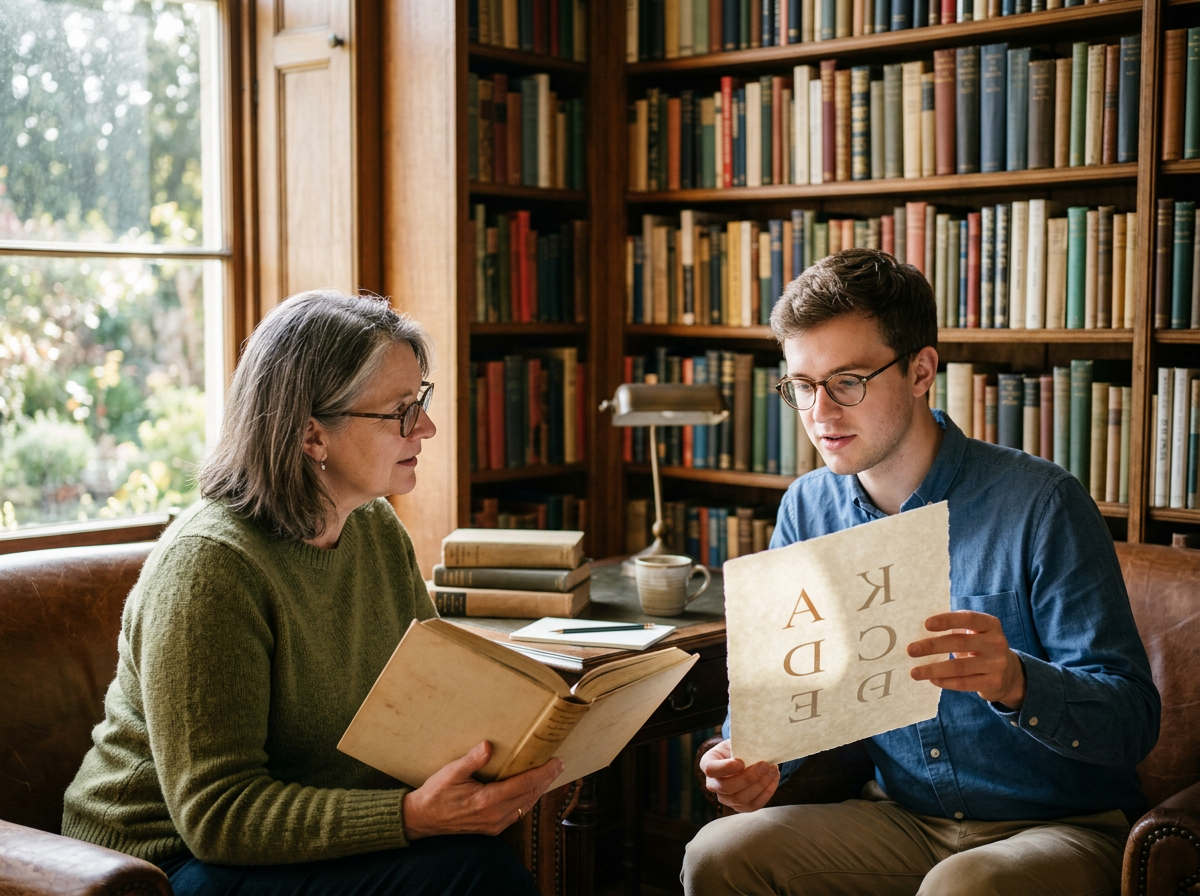
Welche Schriftarten eignen sich am besten für Bücher?
Die Wahl der passenden Schriftart für ein Buch stellt eine entscheidende Weichenstellung dar, die weit über bloße Ästhetik hinausgeht. Ein falscher Schriftsatz kann die Leseerfahrung erheblich beeinträchtigen, Ermüdungserscheinungen fördern und sogar die Botschaft des Textes verwässern.
Oftmals wird die Bedeutung der Typografie unterschätzt, dabei beeinflusst sie maßgeblich, wie flüssig und angenehm der Leseprozess verläuft. Eine gut gewählte Schriftart unterstützt den Inhalt, ohne selbst in den Vordergrund zu treten.
Dieser Leitfaden beleuchtet die kritischen Faktoren bei der Auswahl von Buchschriftarten und zeigt auf, welche Merkmale eine optimale Lesbarkeit gewährleisten, damit jedes Werk seine volle Wirkung entfalten kann.
Kurz zusammengefasst
- Serifen-Schriften wie Garamond oder Times New Roman bieten optimale Lesbarkeit für Fließtexte in Büchern.
- Die Schriftgröße sollte zwischen 10 und 12 Punkt liegen, der Zeilenabstand bei 120-145 % der Schriftgröße.
- Kontrast und Satzspiegel beeinflussen die visuelle Ermüdung stärker als die reine Schriftwahl.
- Für Überschriften und Zitate sind serifenlose Schriften oder Akzentschriften denkbar, jedoch sparsam eingesetzt.
Welche Eigenschaften machen eine Schriftart für Bücher lesefreundlich?
Lesefreundliche Schriftarten für Bücher zeichnen sich durch eine hohe Erkennbarkeit der einzelnen Zeichen und einen harmonischen Rhythmus im Fließtext aus, was die visuelle Verarbeitung des Textes durch das Auge erleichtert und Ermüdung vorbeugt.
Die primäre Funktion einer Buchschrift besteht darin, den Inhalt transparent zu vermitteln, ohne die Aufmerksamkeit auf sich zu ziehen. Eine gute Schriftart integriert sich nahtlos in das Leseerlebnis.
Die Rolle von Serifen und deren Wirkung
Serifen sind kleine Querstriche an den Enden der Buchstabenstriche, die traditionell als Lesehilfe dienen. verbinden die Buchstaben optisch zu Wörtern und Zeilen, was den Augenfluss über längere Textpassagen hinweg fördert.
Klassische Serifen-Schriften wie Garamond oder Caslon gelten seit Jahrhunderten als Standard für gedruckte Bücher. die feinen Details tragen zur Unterscheidbarkeit ähnlicher Buchstaben bei.
Die psychologische Wirkung von Serifen-Schriften wird oft mit Tradition, Seriosität und Beständigkeit assoziiert. Für Belletristik oder Sachbücher, die eine gewisse Autorität vermitteln sollen, sind sie daher eine bevorzugte Wahl.
Schriftgröße und Zeilenabstand optimal einstellen
Die Schriftgröße ist ein entscheidender Faktor für die Lesbarkeit; für den Haupttext in gedruckten Büchern hat sich eine Größe von 10 bis 12 Punkt etabliert, abhängig vom Schriftbild und der Zielgruppe.
Ein angemessener Zeilenabstand, auch als Durchschuss bezeichnet, verhindert, dass sich die Zeilen optisch überlappen und verbessert die Trennung der Textzeilen. Werte zwischen 120 % und 145 % der Schriftgröße sind hierfür praxisbewährt.
Ein zu geringer Zeilenabstand führt zu einem dichten Textblock, der das Auge überfordert, während ein zu großer Abstand den Textfluss unterbricht und die Kohärenz der Absätze stört.
Kurz gesagt: Lesefreundlichkeit in Büchern resultiert aus gut erkennbaren Serifen-Schriften, einer optimalen Schriftgröße zwischen 10 und 12 Punkt sowie einem angepassten Zeilenabstand von 120-145 %.
Welche Schriftarten haben sich in der Buchproduktion bewährt?
In der langen Geschichte des Buchdrucks haben sich bestimmte Schriftarten aufgrund ihrer hervorragenden Lesbarkeit und ästhetischen Qualitäten als Standard etabliert, die auch heute noch vielfach zum Einsatz kommen.
Diese bewährten Schriften bieten eine ausgewogene Mischung aus Tradition, Klarheit und visueller Harmonie, die für lange Lesepassagen unerlässlich ist.
Klassiker der Serifen-Schriften für Fließtext
Die Garamond, benannt nach dem französischen Schriftgießer Claude Garamond, ist eine der elegantesten und am häufigsten verwendeten Schriften in der Buchgestaltung. die feinen Proportionen und die sanften Serifen verleihen ihr eine zeitlose Anmutung.
Eine weitere Ikone ist die Caslon, deren Ursprünge im 18. Jahrhundert liegen. besticht durch die Robustheit und Klarheit, was sie besonders für klassische Literatur und wissenschaftliche Werke geeignet macht.
Die Times New Roman, ursprünglich für die Londoner Zeitung „The Times“ entwickelt, bietet eine hohe Zeicheneffizienz und gute Lesbarkeit auch bei geringeren Schriftgrößen, weshalb sie in vielen Publikationen, auch Büchern, Verwendung findet.
Praxis-Tipp
Experimentieren mit verschiedenen Schnitten (Regular, Italic, Bold) innerhalb einer Schriftfamilie, um Hierarchien zu schaffen, ohne die Grundschrift zu wechseln.
Serifenlose Alternativen für spezifische Anwendungen
Obwohl Serifen-Schriften den Fließtext dominieren, finden serifenlose Schriften, sogenannte Grotesk-Schriften, die Berechtigung in bestimmten Buchbereichen.
Eine sorgfältig ausgewählte Schriftart, kombiniert mit einem durchdachten Layout, kann ein Buch von einem bloßen Textdokument in ein ästhetisch ansprechendes und leicht zugängliches Leseerlebnis verwandeln.
Letztlich dient die Typografie dem Inhalt. Wenn die Schrift die Aufgabe erfüllt, ohne bemerkt zu werden, dann ist die Gestaltung gelungen. unterstützt den Leser dabei, sich voll und ganz auf die Geschichte oder die vermittelten Informationen zu konzentrieren.